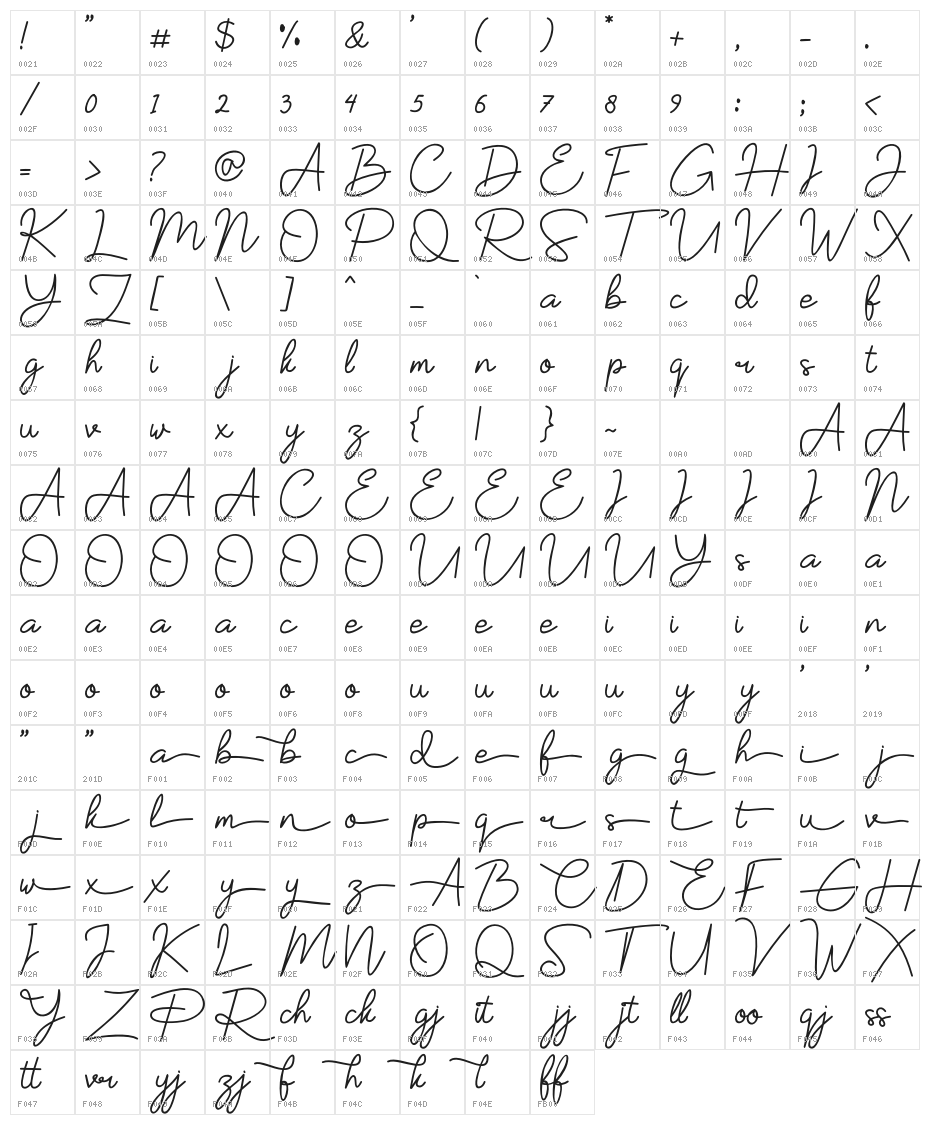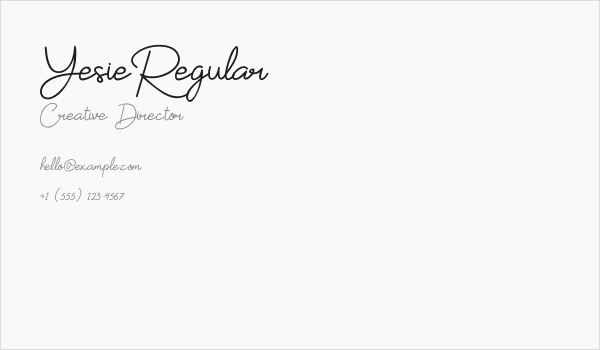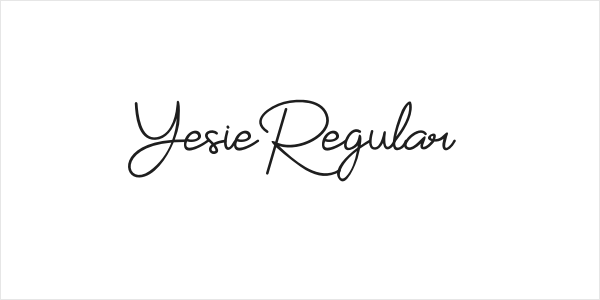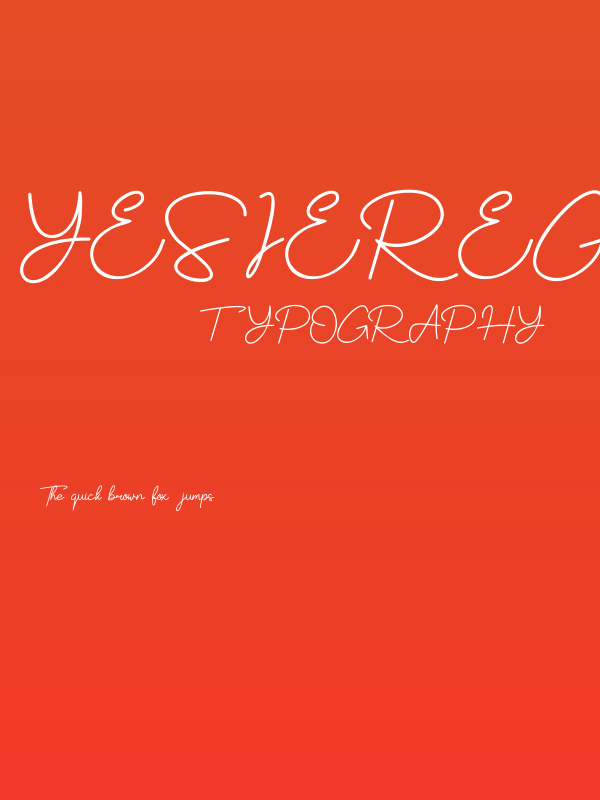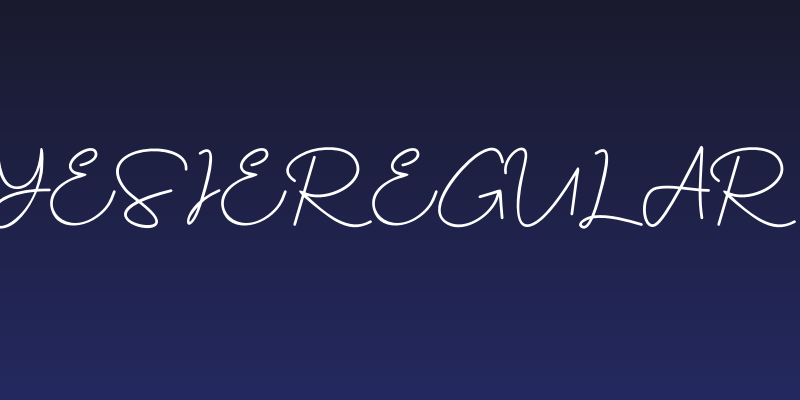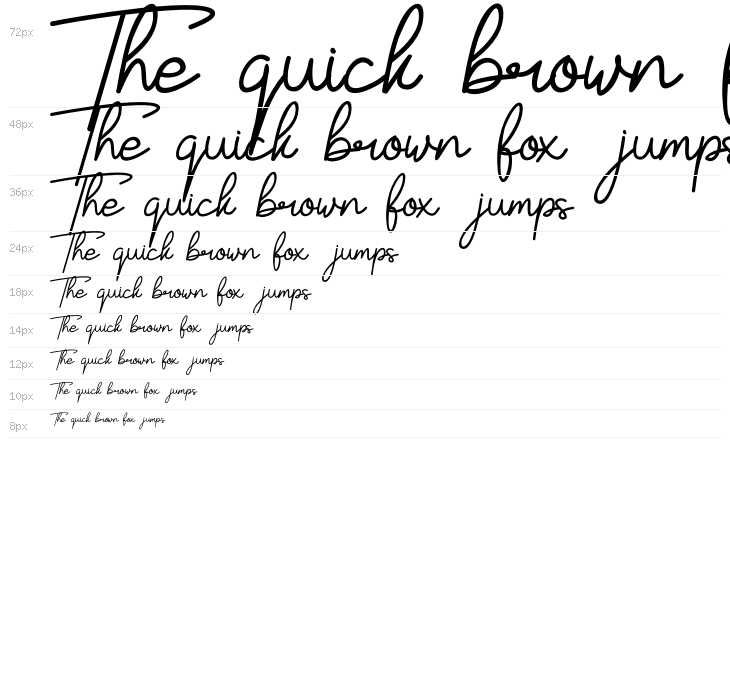
YesieRegular Font
| Caso d'uso | Logos, Invitations, Greeting Cards |
| Progetti proposti | Ideal for wedding invitations, greeting cards, personal branding, and creative projects that require a personal touch. |